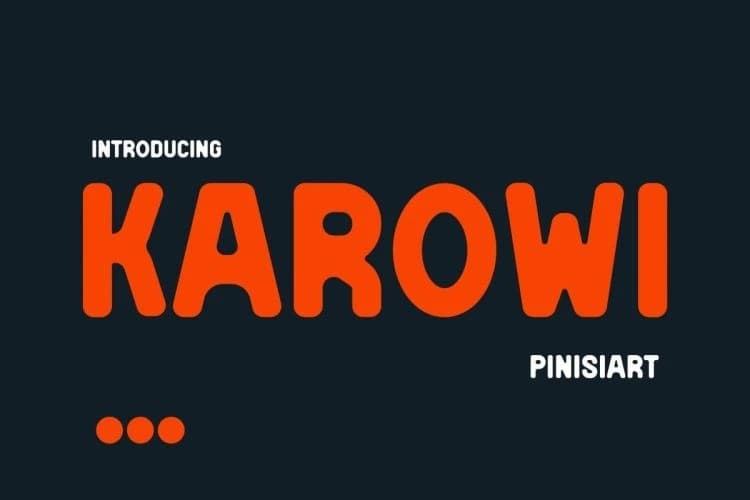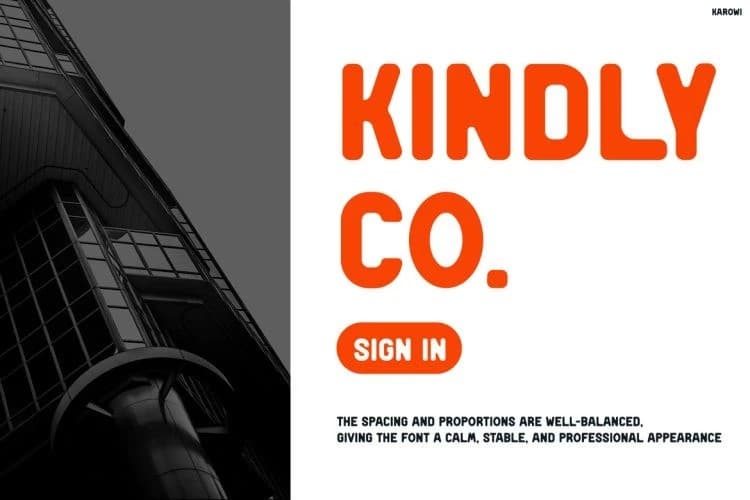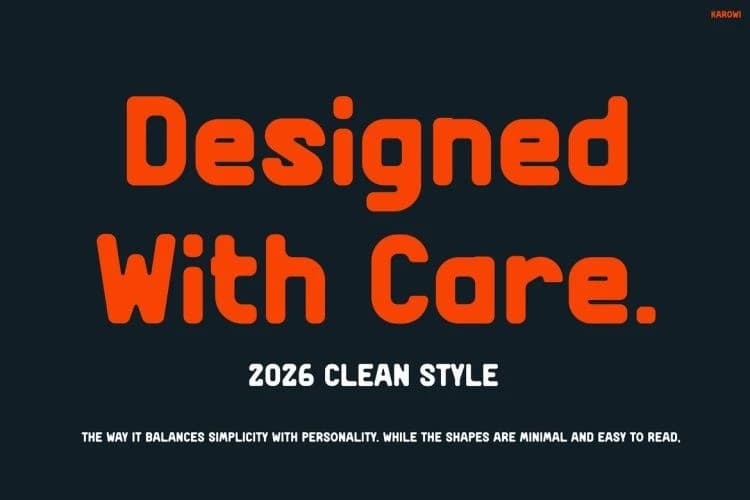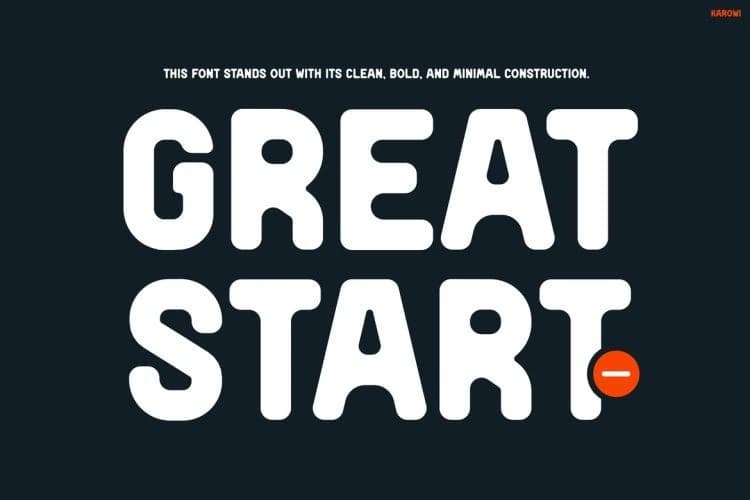
Karowi Font
Karowi Font, kalın ve yuvarlak şekiller ile temiz geometrik dengeyle çarpıcı bir görsel kimlik sunar. Ayrıca, akıcı eğrileri samimi fakat kendinden emin bir ton yaratır; bu da her kelimeyi erişilebilir ve güçlü hissettirir.
Karowi Font, kalın, yuvarlak hatlara sahip temiz geometrik bir dengeyle çarpıcı bir görsel kimlik sunar. Ayrıca, akıcı eğrileri dostça ama kendinden emin bir ton yaratır ve her kelimeyi aynı anda erişilebilir ve güçlü hissettirir.